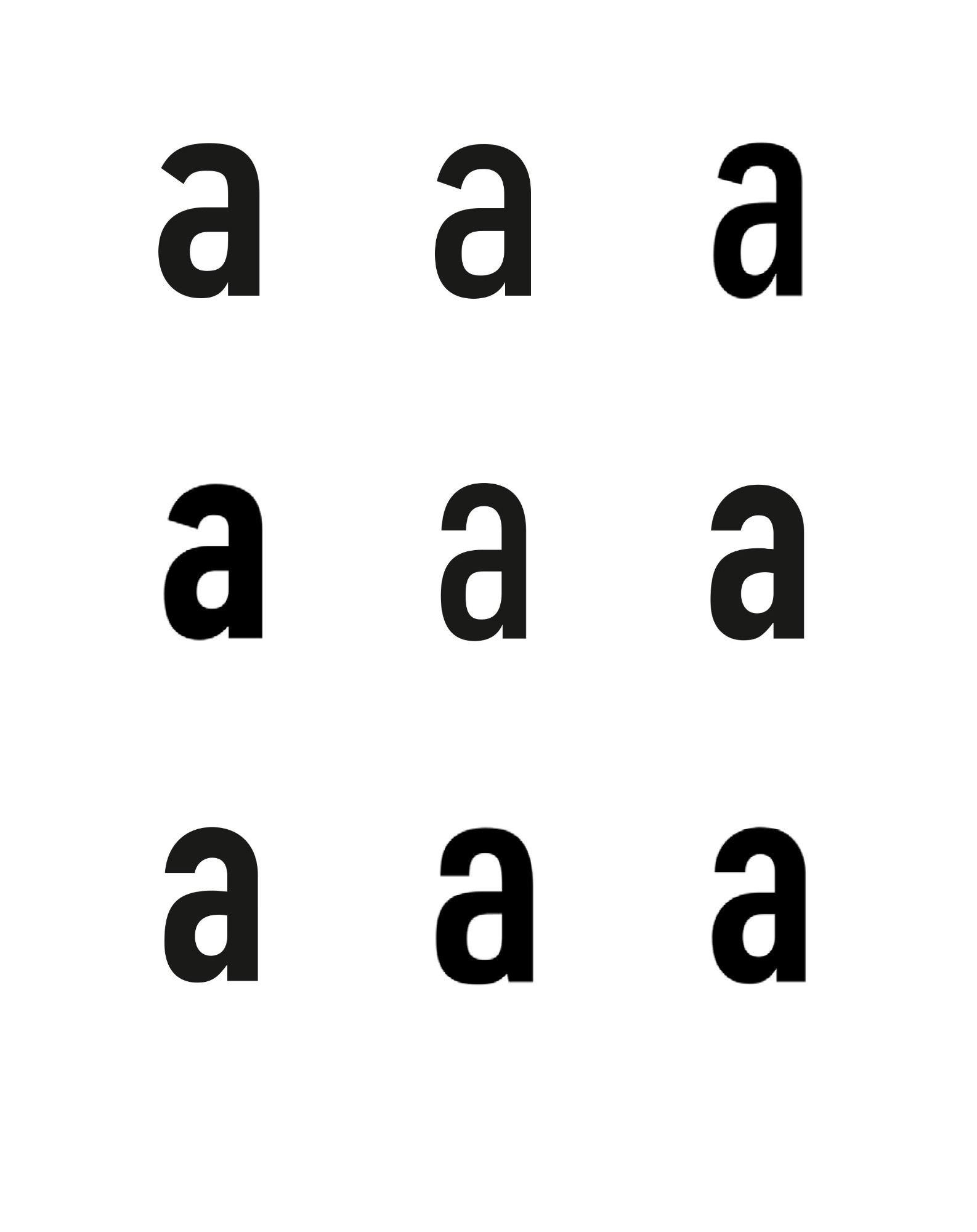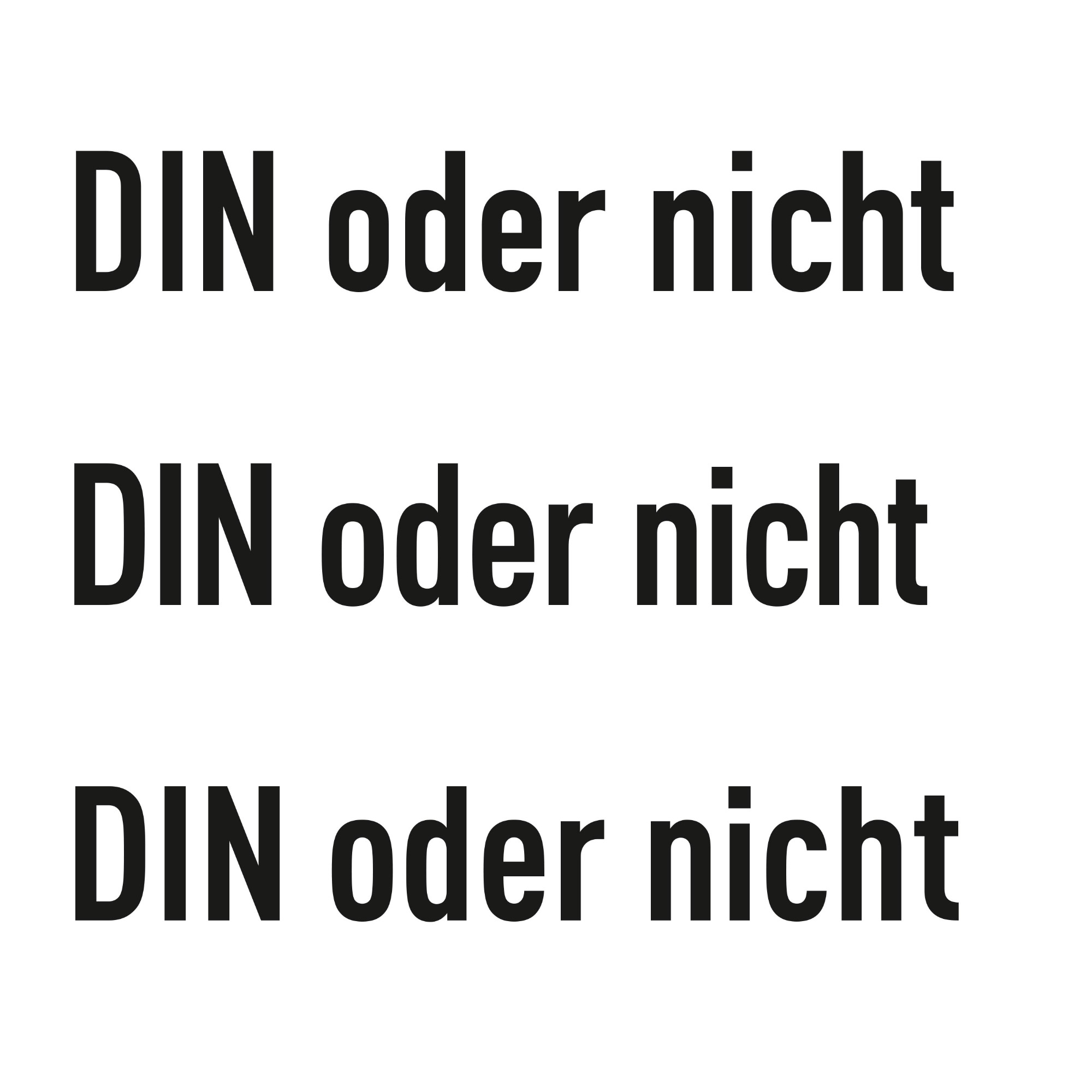
Hast du dir mal den Text zur Neuen DIN durchgelesen?
Den Text habe ich mir auch durchgelesen. Da tun sie sogar als ob sie in die Geschichte der DIN eingetaucht sind, dabei basiert fast alles auf meine Recherchen. Schau mal in deren Quellen-Angaben und lese die von mir geschriebene Dokumente mal nach. Selbst haben sie nichts neues herausgefunden. Das gilt auch für den Hinweis auf die Schrift der Königlichen Preußischen Eisenbahn. Die Idee, dass die Engschrift wahrscheinlich auf die Schrift der KPE basiert, kam zu Stande in einem Gespräch was ich 2004 auf den TypoTagen Leipzig mit Indra Kupferschmid hatte. Sie schickte mir Scans von SW Abbildungen aus dem Buch von Wolfgang Diener zu. Die farbige Originale fand ich im DB Museum in Nürnberg. Veröffentlicht habe ich den Fund 2005 im damaligen Online-Magazin »Encore« und in Typo-Magazine von Filip Blažek. Auch der Hinweis auf Adolf Gropp ist ein Ergebnis meiner Bemühungen. Die Unterlagen schickte mir jemand von der TGM zu, nachdem sie einer meine Vorträge über die Geschichte der DIN-Schriften gesehen hatte.
Da tun sie sogar als ob sie in die Geschichte der DIN eingetaucht sind, dabei basiert fast alles auf meine Recherchen.
Jetzt komme ich nicht mehr mit. Was ist verkehrt daran, dass man sich auf dich bezieht? Nach dem du deine Erkenntnisse publiziert hast ist es ja quasi unmöglich, dass jemand deinen Weg noch einmal geht und somit in die Geschichte der »DIN« eintaucht wie du es getan hast. Du hast dein Wissen geteilt und sie haben darauf aufgebaut. Das klingt für mich nach einem normalen und auch sinnvollen Prozess solange die Quellen genannt werden.
Ich zitiere hier mal aus dem Specimen zur Neuen DIN:
Pool succeeded in improving the legibility of continuous text without sacrificing the industrial rawness of the design. To achieve this, he drew the horizontal strokes thinner and made the curves and their transitions to straight lines smoother. Some characters were made rounder, and terminals of the letters, such as c or s, were finished with diagonal ends. Also the x-height increased with the width of the stroke.
Pool’s interpretation is still considered by many today, as the best version of DIN.
OT: Mit dem Paarungsvorschlag (vorletzte Seite) mit der Change bin ich dann aber wirklich nicht einverstanden. 🤪
Aber genau das »originelle« passt doch überhaupt nicht zur DIN.
Die der DIN ähnliche Schriften von Lineto habe ich aus folgenden Gründen als originell bezeichnet:
– Sie sind streng geometrisch aber bauen nicht sklavisch auf dem Raster und Proportionen der DIN 1451 von 1932 oder 1980 auf.
– Sie verfolgen nicht den Ansatz für den ich mich bei der FF DIN entschieden habe: Etwas Strichkontrast und die Entfernung der Geraden in den vertikalen Kurven.
OT: Mit dem Paarungsvorschlag (vorletzte Seite) mit der Change bin ich dann aber wirklich nicht einverstanden. 🤪
Ich auch nicht. Paarungen funktionieren vor allem dann, wenn die Partner formal gesehen ein deutlichen Gegensatz bilden. Sowohl stilistisch als auch in Strichstärke und/oder Schriftweite.
Alternativ können Sie ein sogenanntes Gegensatzpaar bilden. Also ebenfalls ein formalen Gegensatz, aber als Paar erkennbar. Das funktioniert innerhalb einer Superfamilie bzw. Schriftsippe Mit etwas Geschick auch wenn beide gleiche Klassifikationsmerkmale wie klassizistisch/statisch/Modern Face/Spitzfederkontrast oder Renaissance/dynamisch/old style/humanist aufweisen. Siehe Kupferschmid. Die Kategorien Sans oder Serif enthalten beide Kontrastarten und garantieren somit kaum die Bildung eines erkennbaren Paares. Was meiner Meinung nach geht ist Garamond oder Times für Text und (schmal-) fette Bodoni für die Überschriften. Change für Text und schmalfette DIN für Überschriften bilden zwar halbwegs einen Gegensatz aber kein erkennbares Paar. Sie vermitteln zu wenig gemeinsame Charakteristika.
zwar halbwegs einen Gegensatz
Hmmm – Sans, ähnlicher Kontrast, superelliptisch? 😉
Interessant, aber auch derart diffizil, dass man da schon tiefer in der Materie stecken muss, dass es auch passt, oder. ;-)
Und Nummer 1 würde ich auch eher als zweitbeste Wahl bezeichnen, wenn zum Beispiel keine optische Größen zur Hand sind. :-|
Ich schau mir gerade die DIN 1451 an und kann dem beim besten Willen nicht zustimmen. Konstruiert ist für mich die PDU aber bei der DIN gibt es so viele Details die eben nicht konstruiert sind oder zumindest nicht so wirken.
die DIN ist aber nicht nur 1451. Wie ich schrieb: "... wenn man sich die geschichte der DIN anschaut ist da alles dabei was irgendwie konstruiert, schnell erfassbar ..."
wie gesagt, es ist die sicht meiner dinge und für mich haben die zusätzlichen schnitte nicht mehr viel mit DIN gemeinsam.
Ich verstehe, dass sich die XX-Schnitte nicht direkt wie eine klassische DIN anfühlen. Aber wäre das überhaupt möglich gewesen und ist das 2023 nötig?
dann einfach nicht DIN nennen und fertig. 😉
Wenn die Vito mehr DIN ist als die Neue DIN dann komme ich ehrlich gesagt nicht mehr mit ...
das habe ich nicht behauptet, bzw. hast du mich falsch verstanden.
ich wollte damit nur zum ausdruck bringen, dass diese XX formen so weit weg vom standard schnitt sind, das ich dann auch eine vito, univers etc. DIN nennen könnte.
Es gab sicher technisch bedingt gravierte DIN-Varianten oder auch DIN-Schablonen die quasi Rounded waren. Aber die FF DIN Round wurde auf Basis der FF DIN gestaltet und nicht auf Basis historischer Vorlagen – so kann man das zumindest bei MyFonts nachlesen.